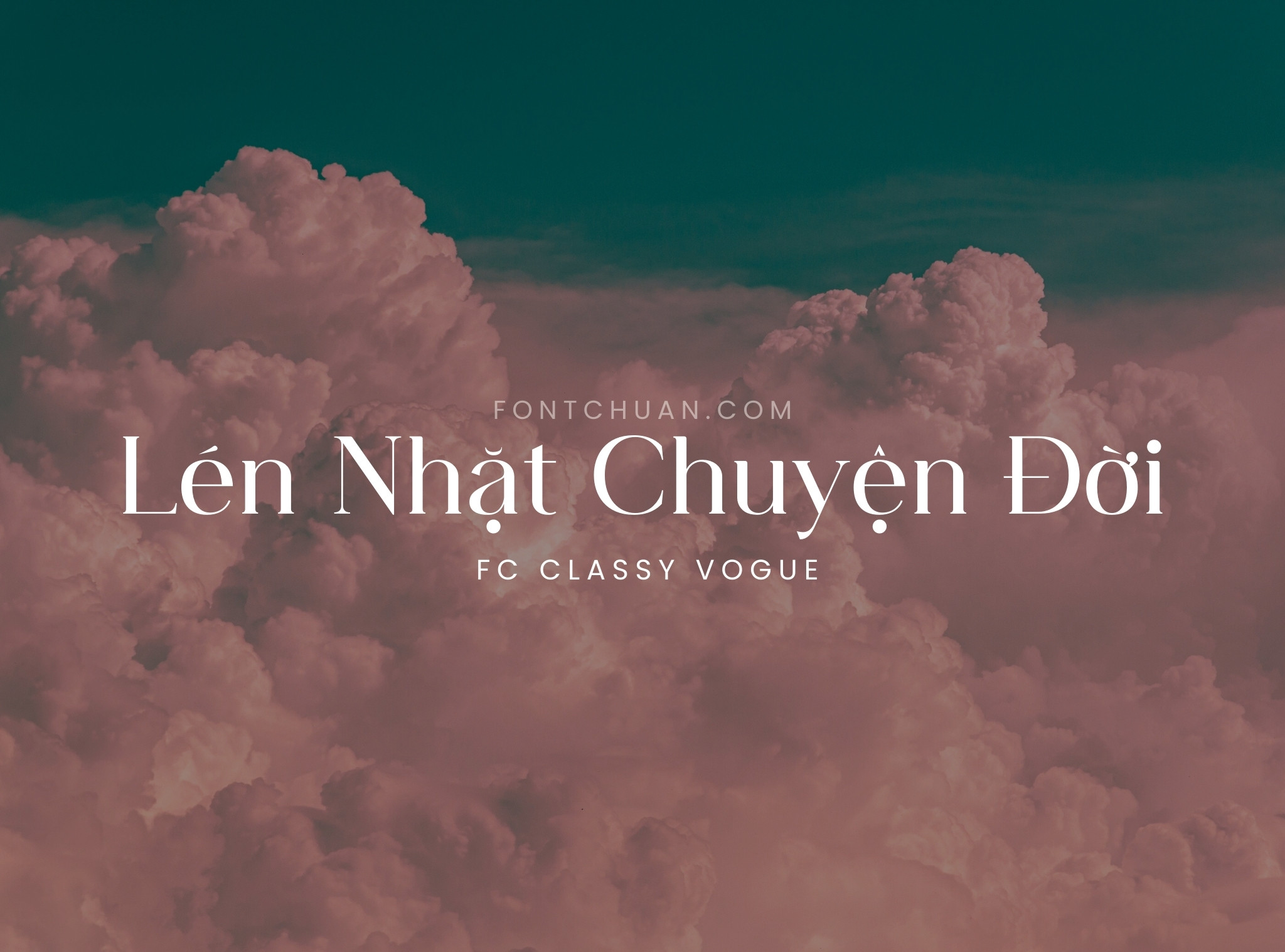
Classy Vogue là một kiểu chữ serif mang phong cách thanh lịch và hiện đại, được thiết kế bởi Variatype. Font này ra mắt vào năm 2022, lấy cảm hứng từ các kiểu chữ thời trang cao cấp với các đường nét thanh mảnh nhưng đầy cá tính. Với sự hỗ trợ lên đến 66 ngôn ngữ, font này có thể sử dụng linh hoạt trong nhiều thiết kế sáng tạo.
Font Classy Vogue được ứng dụng rộng rãi trong nhiều dự án vì sở hữu nét chữ mảnh mai nhưng sắc sảo, kết hợp giữa độ cong mềm mại và độ tương phản cao giữa các nét dày và mỏng, tạo nên vẻ sang trọng. Ngoài các thiết kế logo, thương hiệu, bìa tạp chí, poster, quảng cáo thời trang và làm đẹp, font này cũng rất phù hợp cho font chữ Tết, như thiệp chúc mừng năm mới, banner trang trí Tết hay các ấn phẩm in ấn dịp lễ, giúp mang lại không khí tươi vui, sang trọng và hiện đại cho các thiết kế mùa lễ hội.